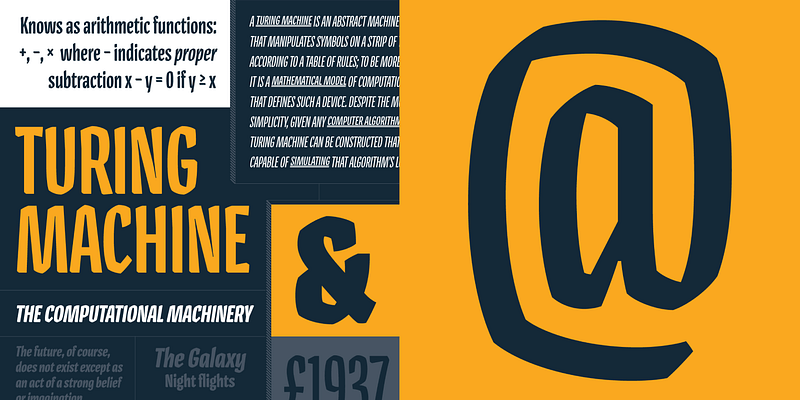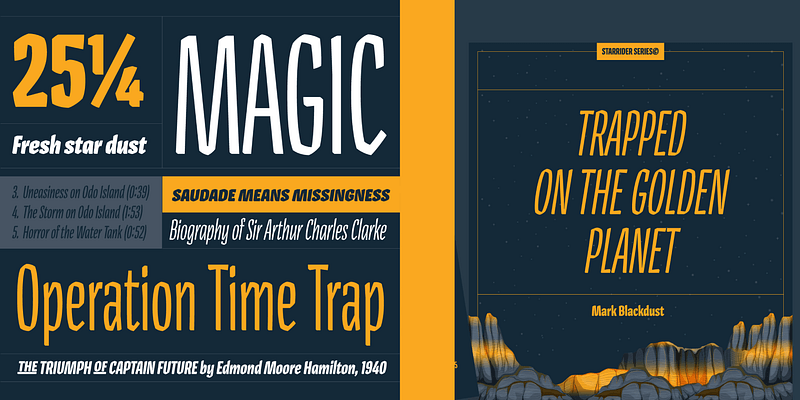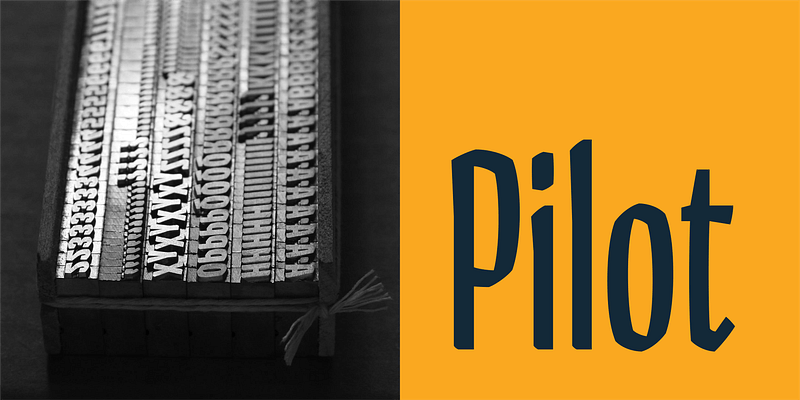
Aleksandra Samuļenkovas markante, schmal laufende Akzidenzschrift geht auf ein Projekt aus ihrem Studium der Typografie und Medien an der KABK in Den Haag zurück und erhielt unmittelbar nach der Veröffentlichung Auszeichnungen, wodurch Samuļenkova zu einer Designerin wurde, die man im Auge behalten sollte. Die Schriftfamilie umfasst fünf Strichstärken mit passender Kursivschrift sowie zwei Varianten von Kapitälchen: Standardkapitälchen, die auf der Grundlinie stehen, und hochgestellte und unterstrichene Kapitälchen. Kontextbezogene Alternativen für „j“, „t“ und „f“ ermöglichen einen noch engeren Satz für schwierige Buchstabenkombinationen. Dieses eckige, facettierte Schrift wirkt fast wie aus Eisen geschlagen und erinnert an eine Zeit, als Schilder von Hand bemalt wurden – und dennoch ist sie absolut zeitgemäß. Verwenden Sie sie für Branding, Überschriften, Verpackungen oder kurze, ausdrucksstarke Textblöcke. Bold Monday, 2012–2017.